文字の名前とグリフの名前02「文字とは何か」
「文字とは何か」などと言い出すと、ちょっと哲学的な話に向かったりしがちですが、ここではそういうのは避けて「フォントの世界」における文字の話をします。言い換えれば、広義のコンピュータで扱う文字です。
フォントの世界では、文字コードと紐付いているものが文字(character)です。つまり「あ」と「ぁ」は別の文字、「か」と「が」は別の文字です。一方「辻」という字のしんにょうの点の数が1つでも2つでも、Unicodeの符号位置はどちらも8FBBなので同じ文字です。
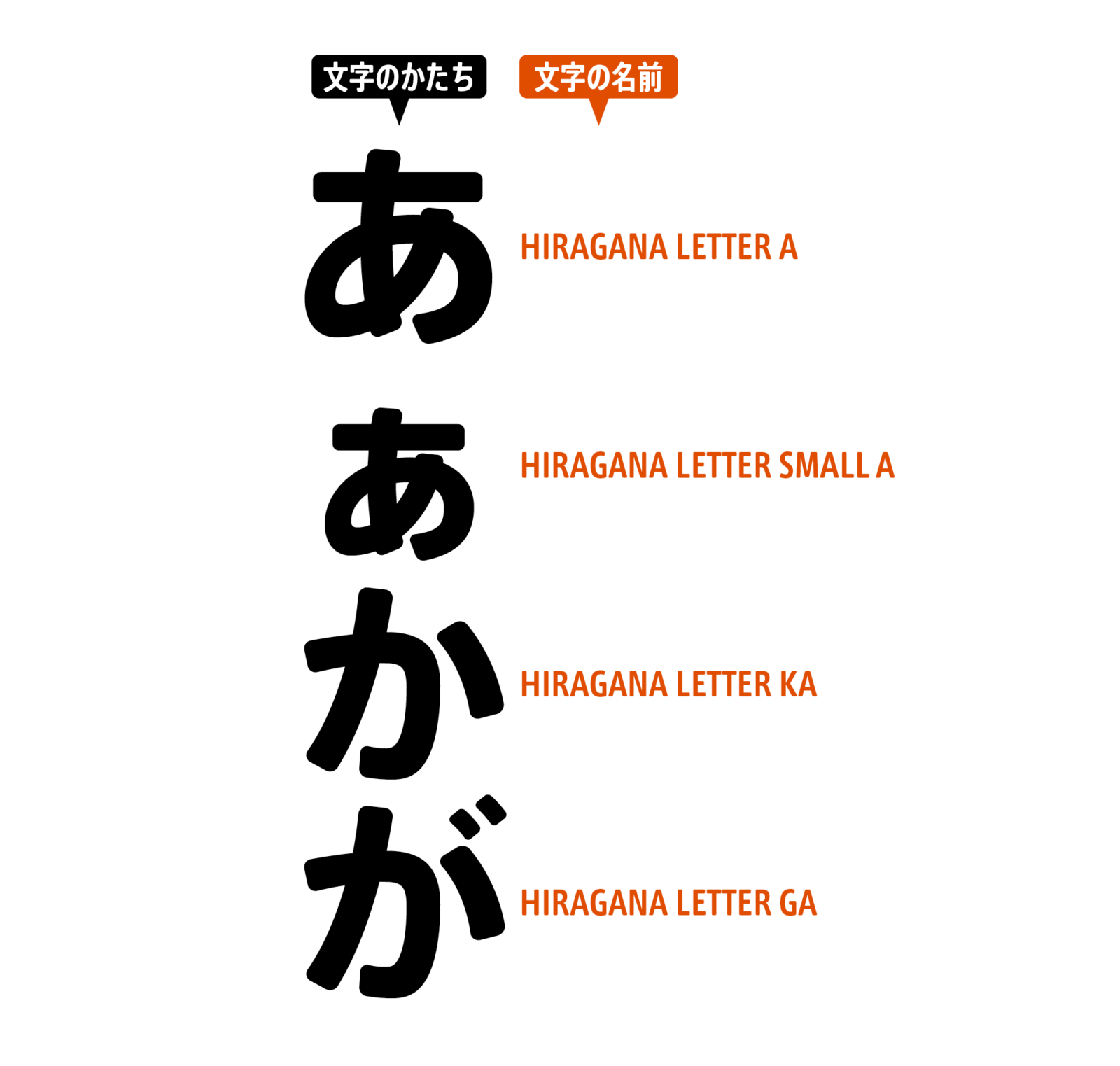
おそらく皆さんの環境では、普通に「つじ」と入力して漢字変換すると二点しんにょうの「辻」の方が表示されるのではないかと思います。わたしは文章を作成するときには、昔からMacに入っているOsakaというフォントを使うクセが抜けていないので、今もこの原稿をOsakaで書いています。そのためわたし目の前のディスプレイに表示されているのは一点しんにょうの「辻」です。
次回は、ちょっと寄り道になるかもしれませんが、「なぜフォントによって同じ字が一点しんにょうだったり二点しんにょうだったりするのか」という点に触れておきたいと思います。